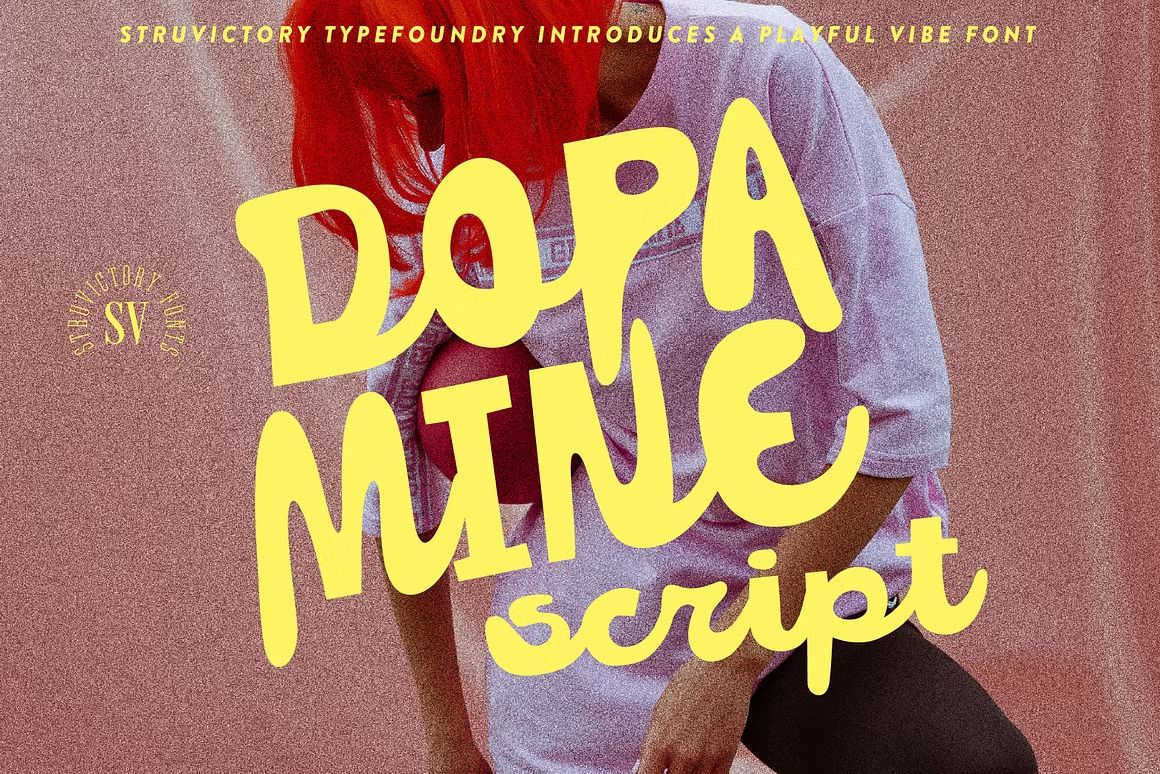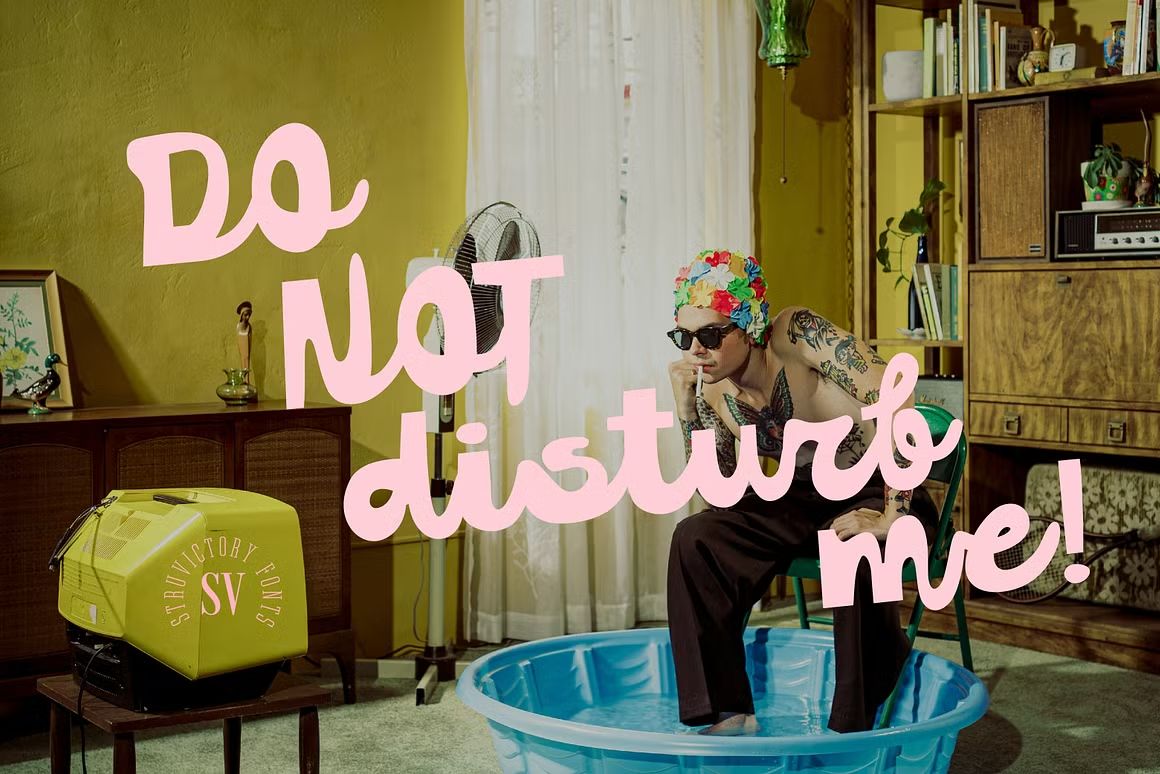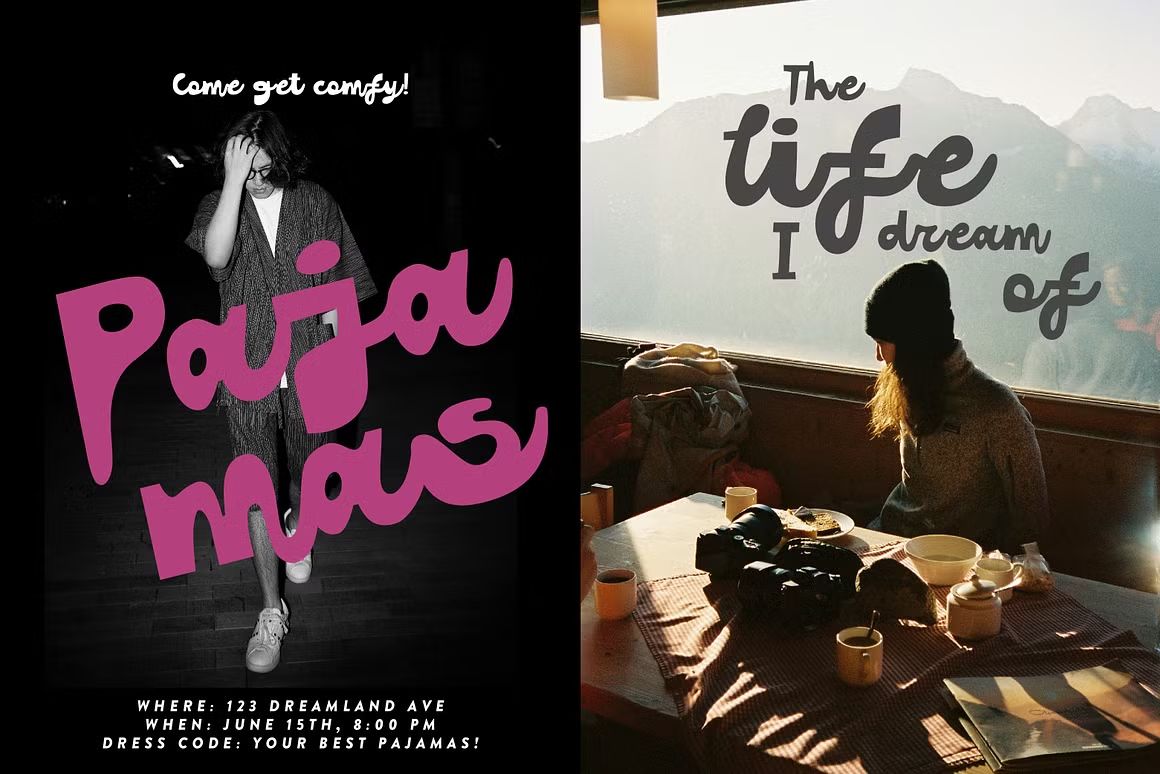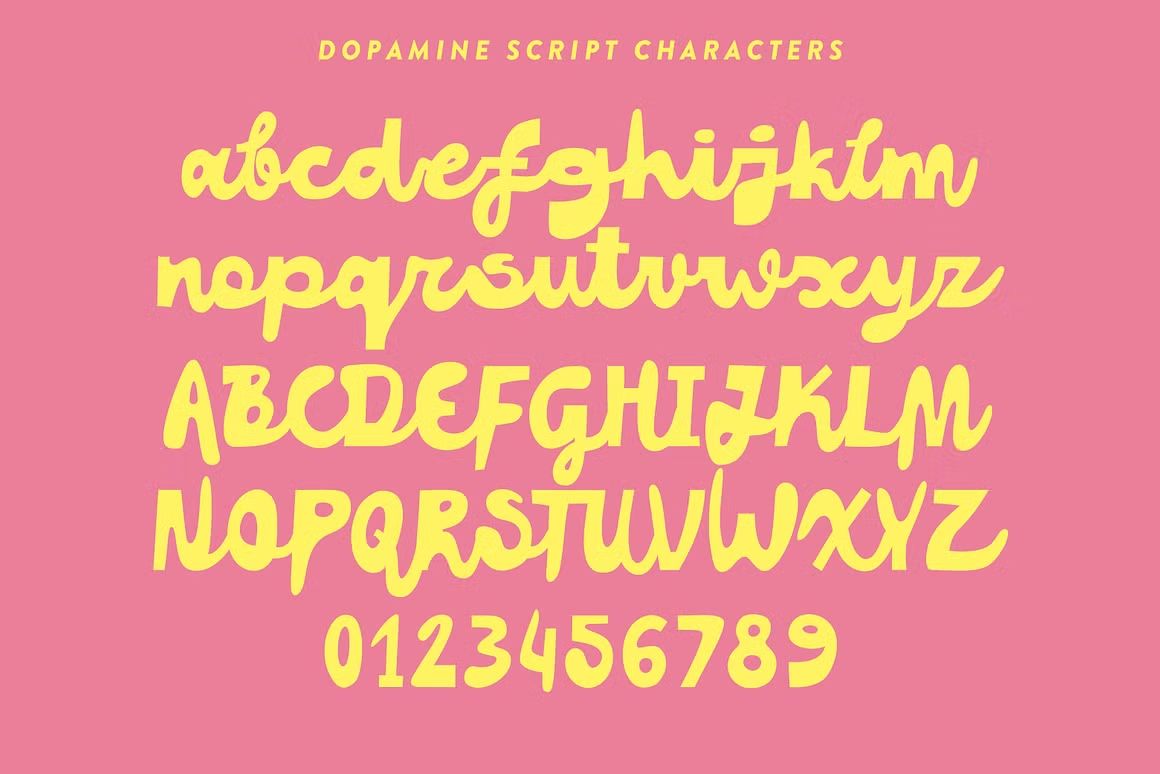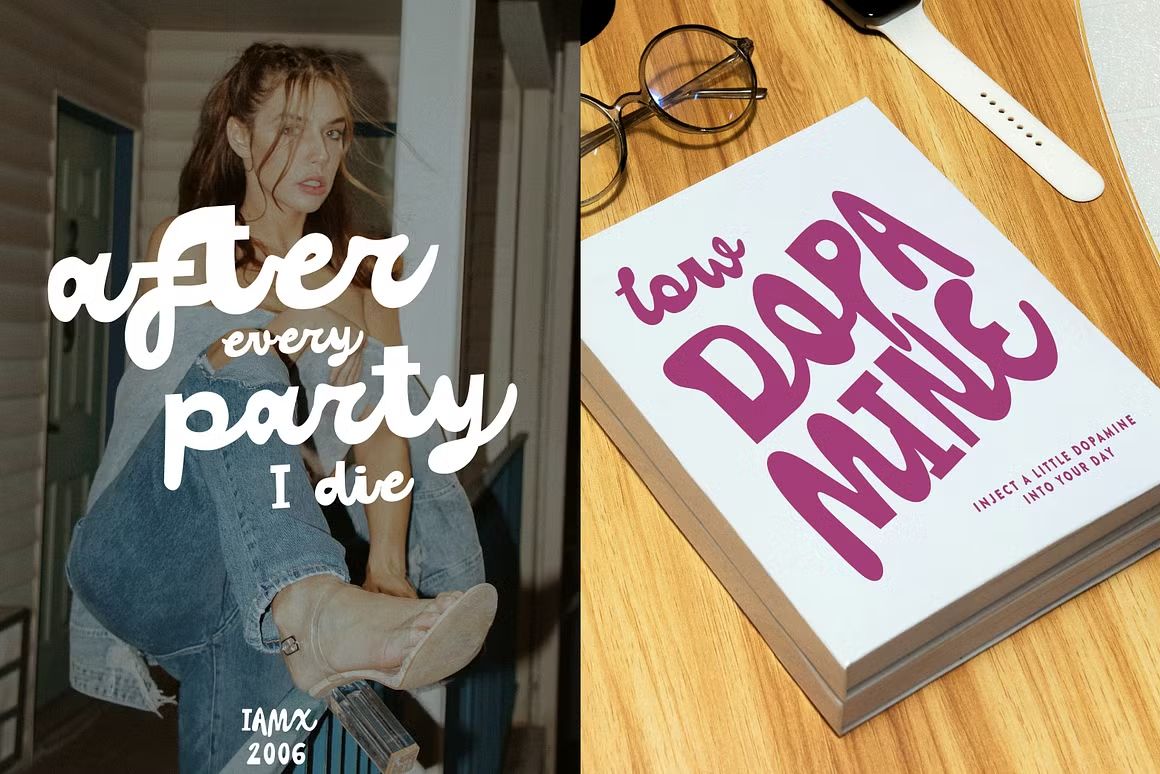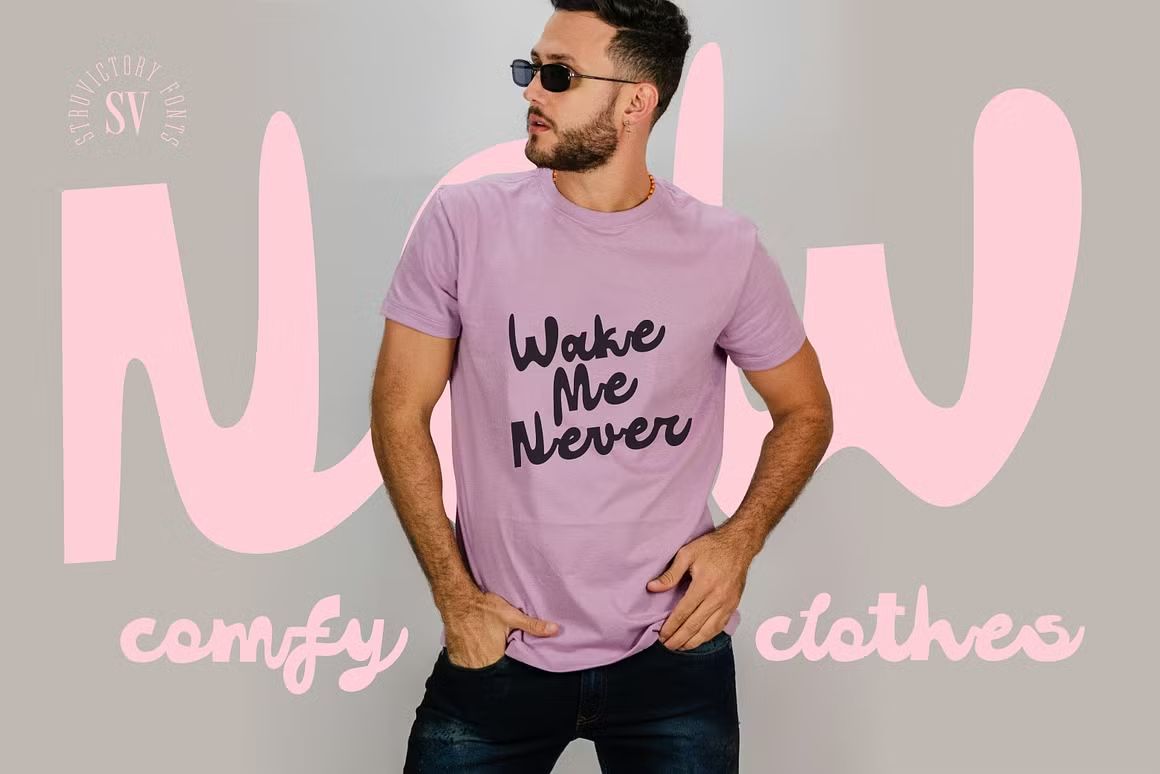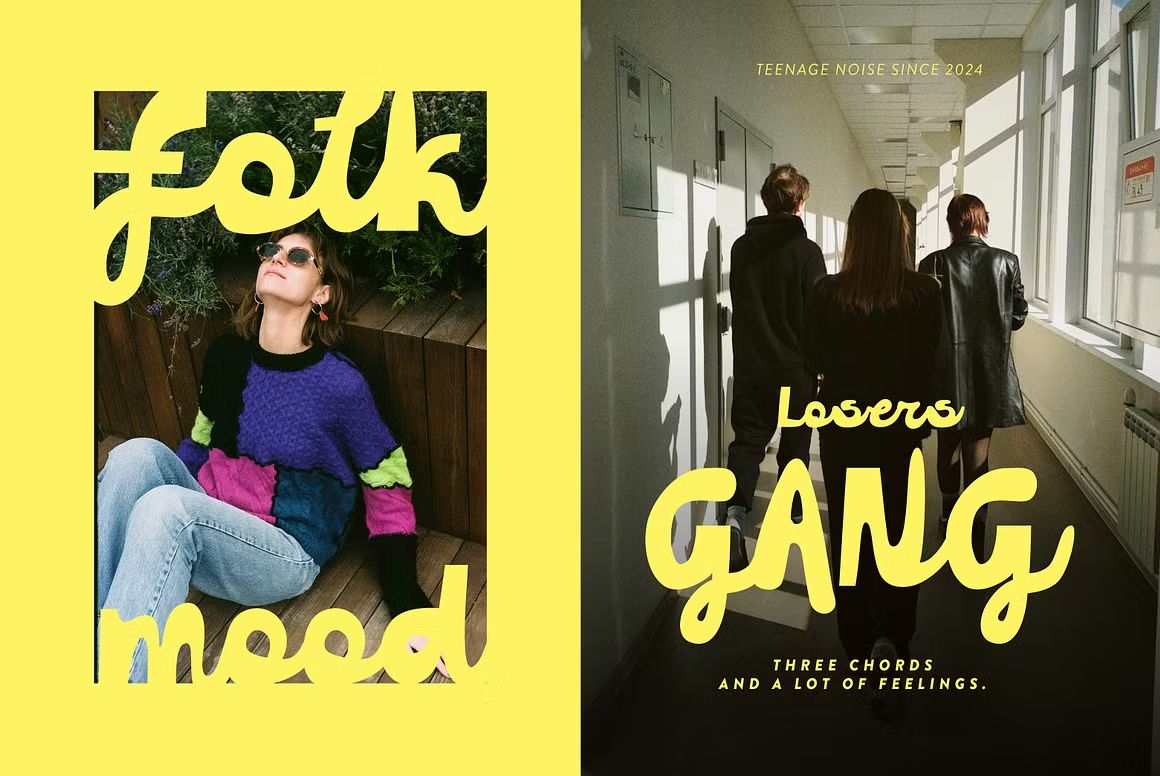
Dopamine – Script Font
Dopamine adalah font script elegan bergaya tulisan tangan modern, cocok untuk branding, undangan, dan media sosial. Format OTF/TTF/WOFF, siap pakai di berbagai desain.
Dopamine adalah font script bergaya modern yang memadukan keanggunan tulisan tangan dengan sentuhan dinamis dan ekspresif. Cocok untuk branding, logo, undangan, kutipan, kemasan produk, dan konten media sosial, font ini menghadirkan nuansa personal namun tetap profesional. Setiap huruf dirancang dengan lengkungan halus dan sambungan yang alami, memberikan kesan elegan dan bersahabat dalam setiap desain.
• Gaya script modern dengan sentuhan tulisan tangan
• Cocok untuk logo, branding, wedding, dan packaging
• Termasuk karakter huruf besar, kecil, angka & simbol